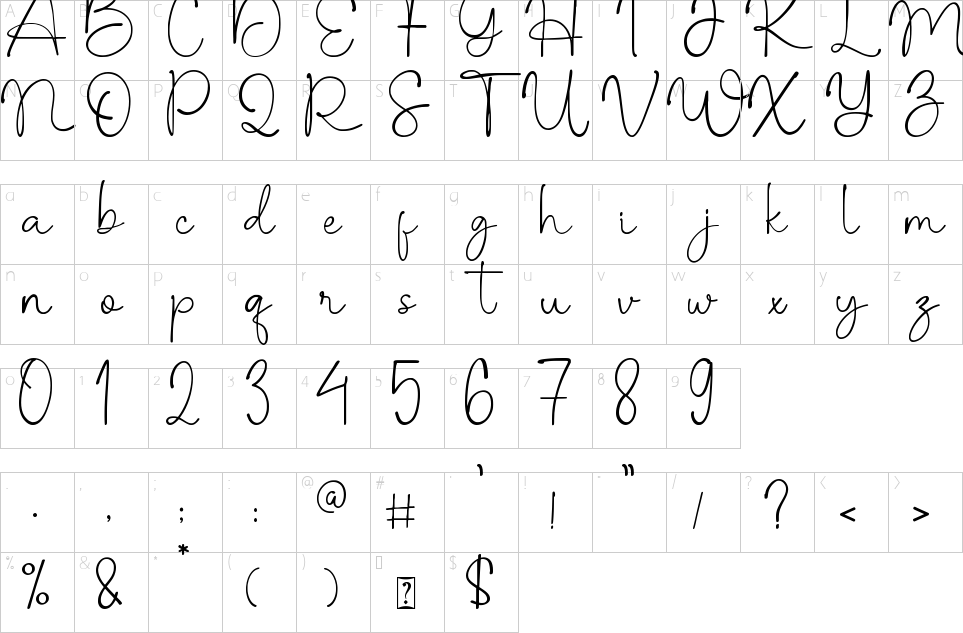
Aqui está uma breve descrição para a página de download da fonte ‘Dreamy Angel’, com 2 parágrafos curtos: Para aqueles que buscam decorações sutis e inspiradoras, a ‘Dreamy Angel’ é perfeitamente adequada. Desenvolvida por Letterara Studio, esta fonte traz nuances suaves e harmoniosas que são uma delícia para os olhos. Com seu design cuidadoso, ela se adapta perfeitamente às criações onde um toque delicado pode fazer toda a diferença – seja em gráficos de newsletter ou até mesmo em desenhos animados. Com o download da ‘Dreamy Angel’ gratuitamente disponível para Windows e Mac, você pode explorar as possibilidades criativas desta fonte única. Com apenas 310 downloads, é uma oferta limitada que merece ser coletada para quem procura algo um pouco diferente na sua coleção de fontes. Através da ‘Dreamy Angel’, sua produção gráfica pode ganhar uma nuance ainda mais romântica e emocional.